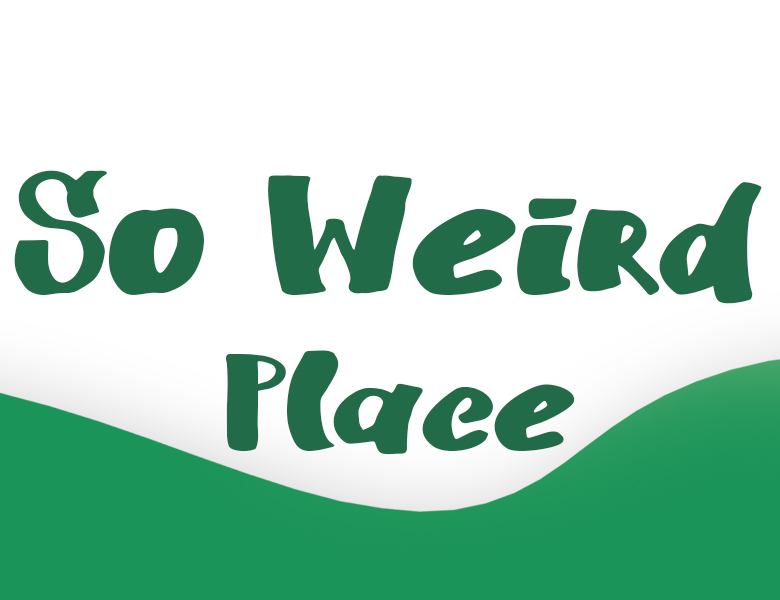
So Weird Place字体
简介:So Weird Place字体是一款稳健大气的英文字体,该字体具有很强的视觉冲击力。适用于广告设计、视频、banner、印刷包装、PPT、文化宣传类等方面的题材。该款字体风格:Regular;字符数:149;字形数:62;字体版本:Version 1.00;March 28, 2021。由站长素材提供免费下载,站长字体下载大全提供精选中英文字体素材。